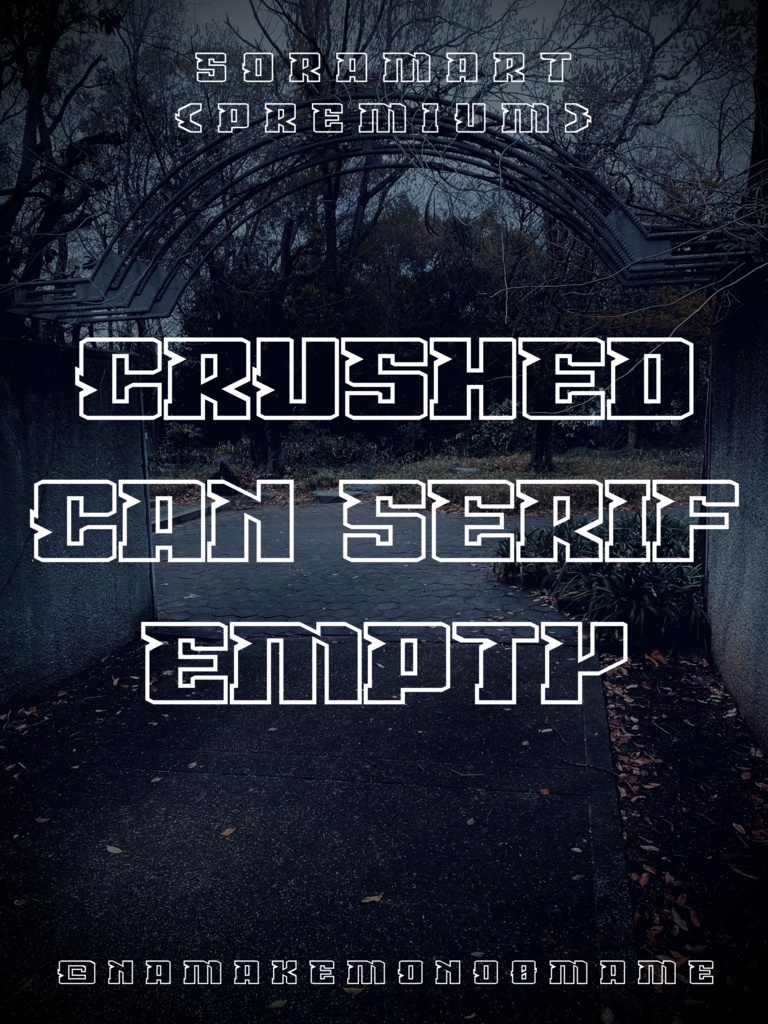
そらマートフォントデータ”Crushed Can Serif Empty”ダウンロード商品¥ 2,500カートに入れるギフトとして贈る「ギフトとして贈る」とはつぶれた空き缶から着想を得たハード太字フォントを白抜きフレーム文字にした "Crushed Can Serif Empty" です。 「TrueTypeフォントファイル」という形式です。 ダウンロードした後、Zipファイル内のデータをインストールしてお使いください。 このフォントは商用利用可となっております。 お客様の制作・創作活動のお役に立てれば幸いです。 ※使用上の注意事項などは、添付のReadmeをお読みください。 ※このフォントは有料販売専用商品です。そらマートFANBOX開設中フォント・書体フォントデータ”RANMMA Drive”そらマート¥ 0フォント・書体フォントデータ”Dandy Laser Max”そらマート¥ 2,500フォント・書体フォントデータ”Dandy Laser”そらマート¥ 2,500フォント・書体フォントデータ”Bubblegum Beat”そらマート¥ 2,500フォント・書体フォントデータ”Caltrop Serif LLL”そらマート¥ 2,500フォント・書体フォントデータ”Caltrop Serif LL”そらマート¥ 2,500フォント・書体フォントデータ”Caltrop Serif”そらマート¥ 2,500フォント・書体フォントデータ”Tonik Crate Super Long”そらマート¥ 2,500フォント・書体フォントデータ”Dot Eat Bug Acid”そらマート¥ 2,500フォント・書体フォントデータ”Dot Eat Bug Mild”そらマート¥ 2,500フォント・書体フォントデータ”Dot Eat Bug”そらマート¥ 2,500フォント・書体フォントデータ”Solid Voltage Strike”そらマート¥ 2,500フォント・書体フォントデータ”Solid Voltage”そらマート¥ 2,500フォント・書体フォントデータ”Henge Edge Rock”そらマート¥ 2,500フォント・書体フォントデータ”Henge Edge Tall”そらマート¥ 0フォント・書体フォントデータ”Henge Edge”そらマート¥ 0フォント・書体フォントデータ”Chisel Stroke Wide”そらマート¥ 2,500フォント・書体フォントデータ”Chisel Stroke”そらマート¥ 2,500フォント・書体フォントデータ”Crushed Can Serif Wide”そらマート¥ 2,500フォント・書体フォントデータ”Crushed Can Serif”そらマート¥ 2,500もっと見る